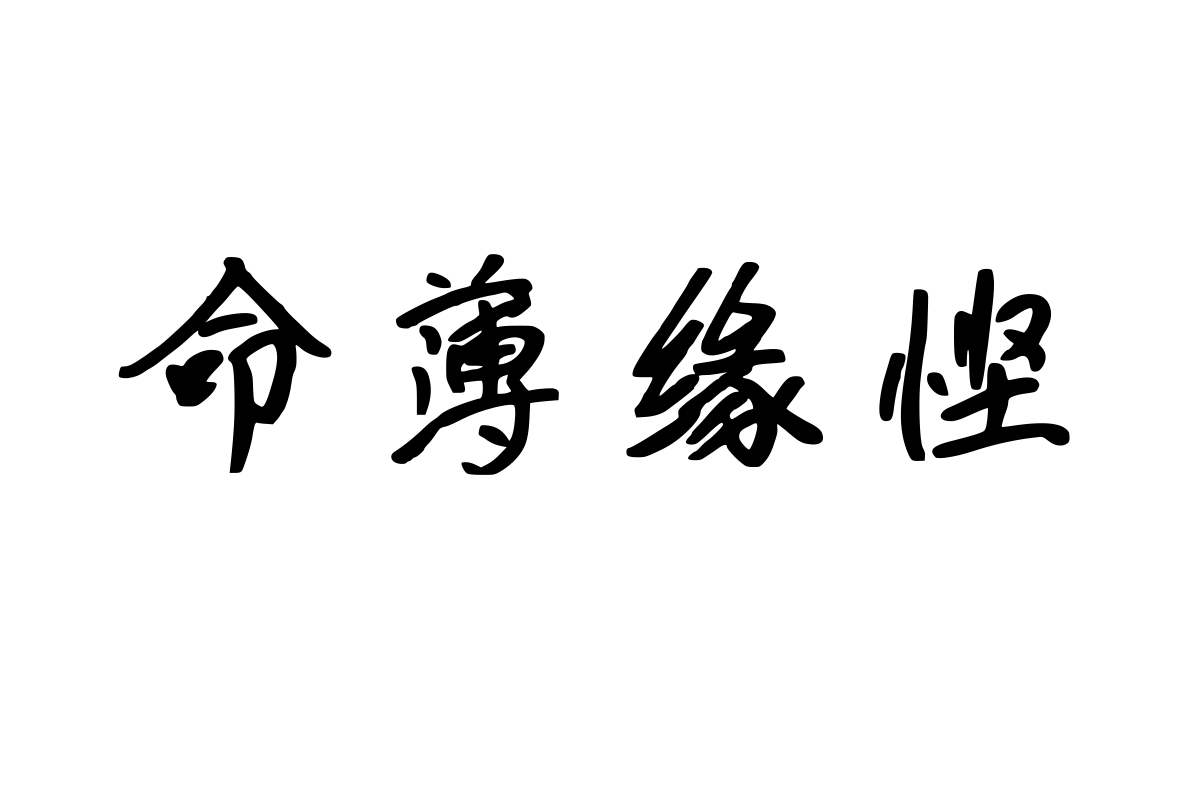
兰米惟愿总相逢字体是一款具有独特韵味的中文字体,其设计风格简约而不失优雅。该字体采用了圆润的笔触和流畅的线条,给人一种温馨而亲切的感觉。同时,字体中还融入了一些传统的元素,如云纹、水波纹等,使得整体风格更加独特。
兰米惟愿总相逢字体适用于各种场景,如广告设计、书籍封面、海报等。它的使用可以使作品更具吸引力和艺术感,展现出独特的魅力。无论是用于商业宣传还是个人创作,兰米惟愿总相逢字体都能为您的作品增色不少。